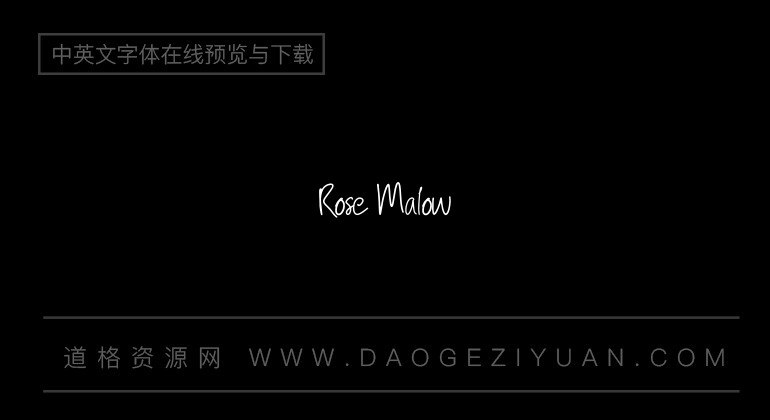
Rose Malow是一款由Fontfabric设计的免费脚本字体,它是一款精美的、轻巧的、多功能的字体,可以用于个性化的文字设计,并且可以满足各种不同的文字需求。Rose Malow具有清晰的线条,精美的细节,可以为文字添加活力和温柔的色彩,以及更多的灵活性和创造力。它可以用于各种文字设计,包括海报、卡片、标识、标题、网页等。内容介绍
Rose Malow是一款非常不错的手写艺术字体,具有很好的视觉感,适合于文化类的宣传设计、商业类品牌的广告和产品包装设计以及个性化文字排版等较多场景。